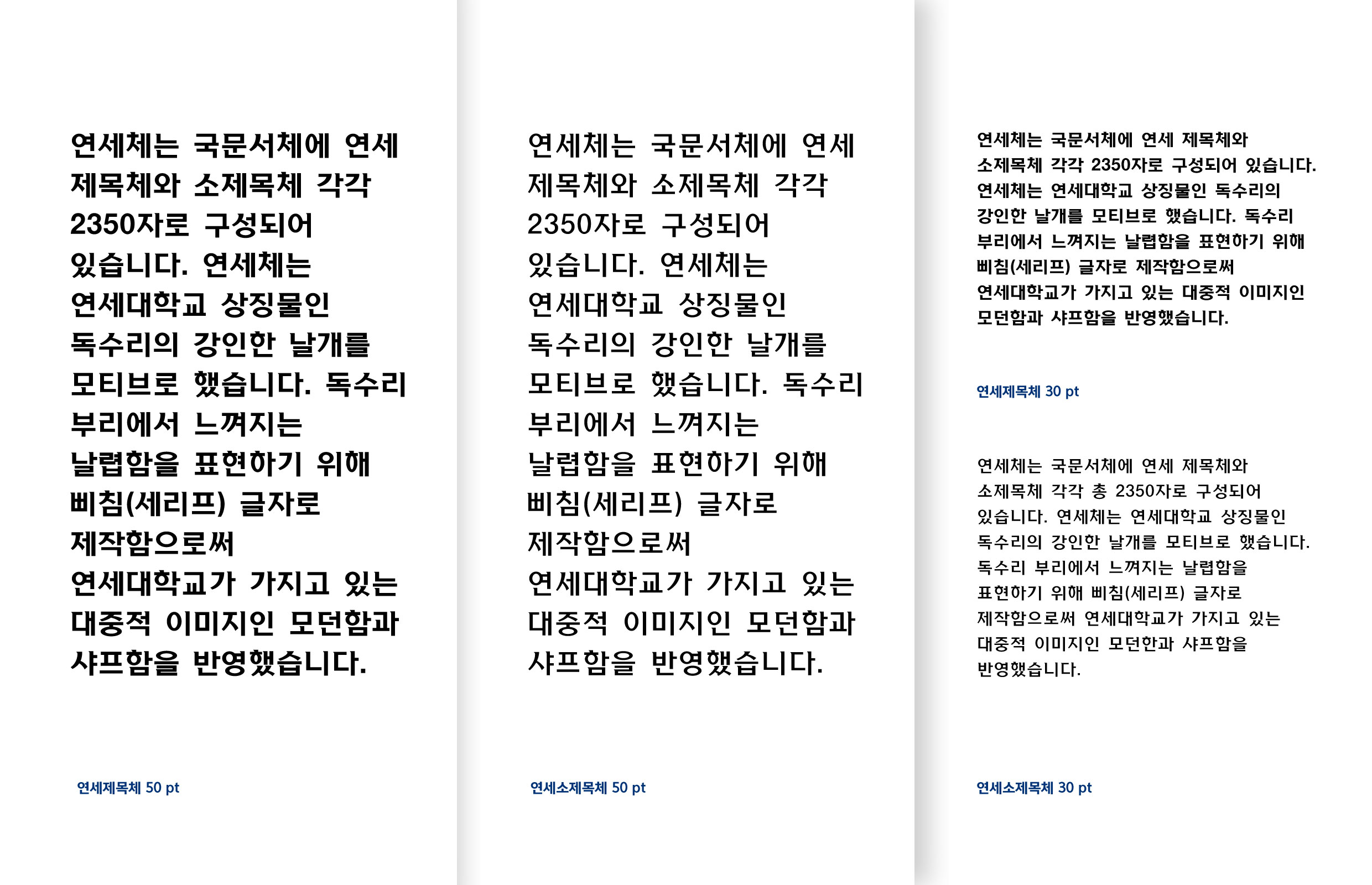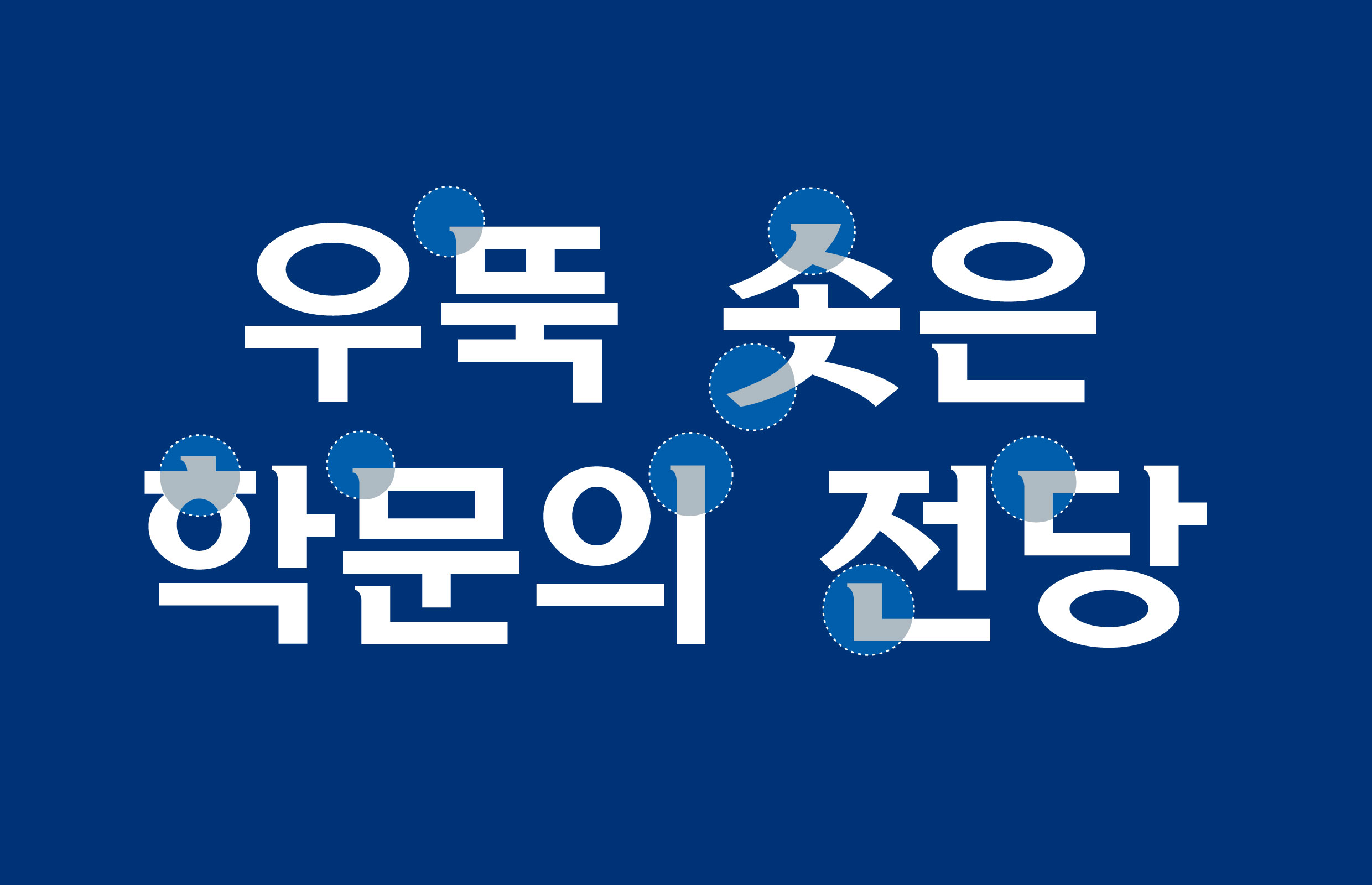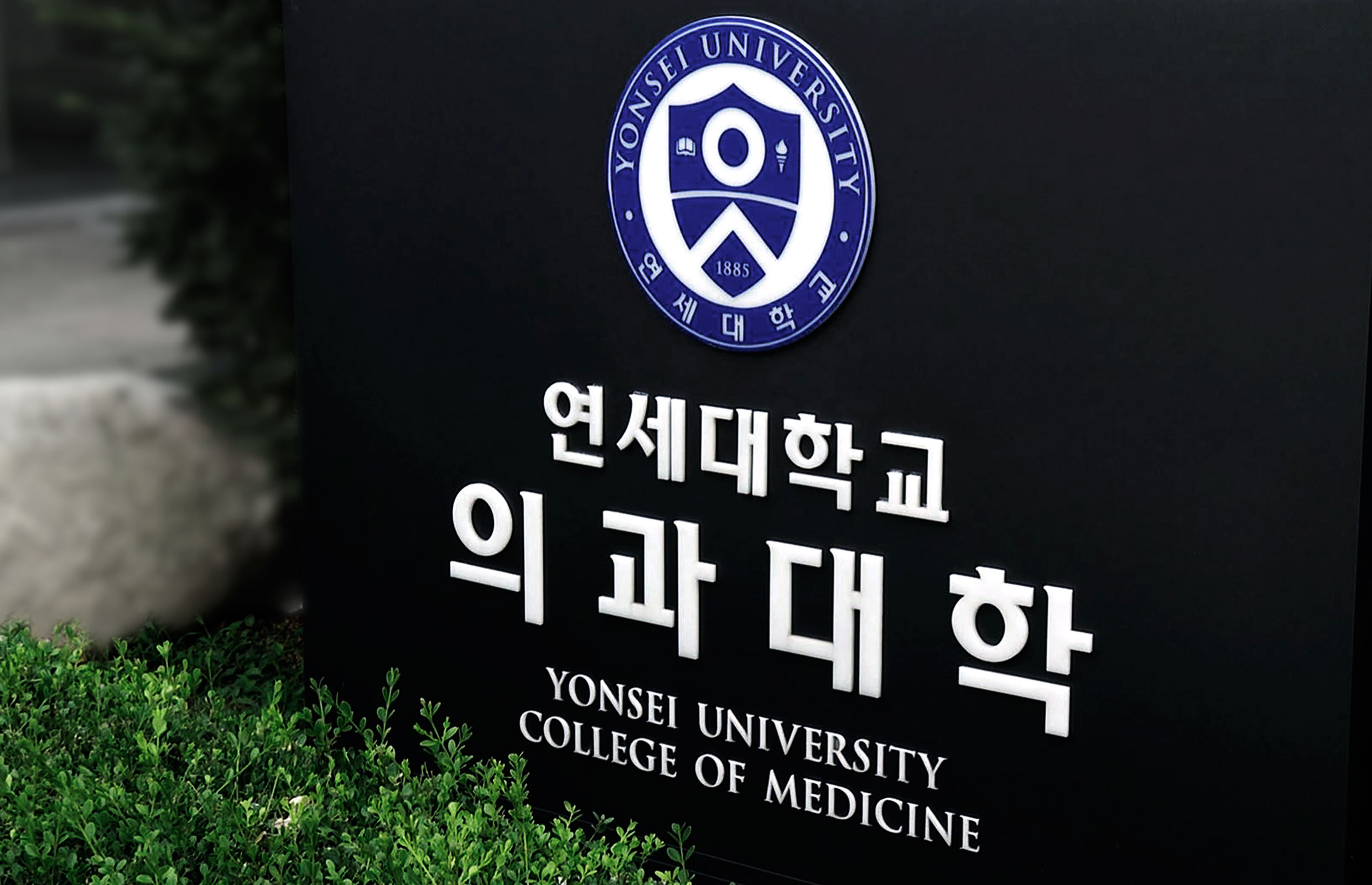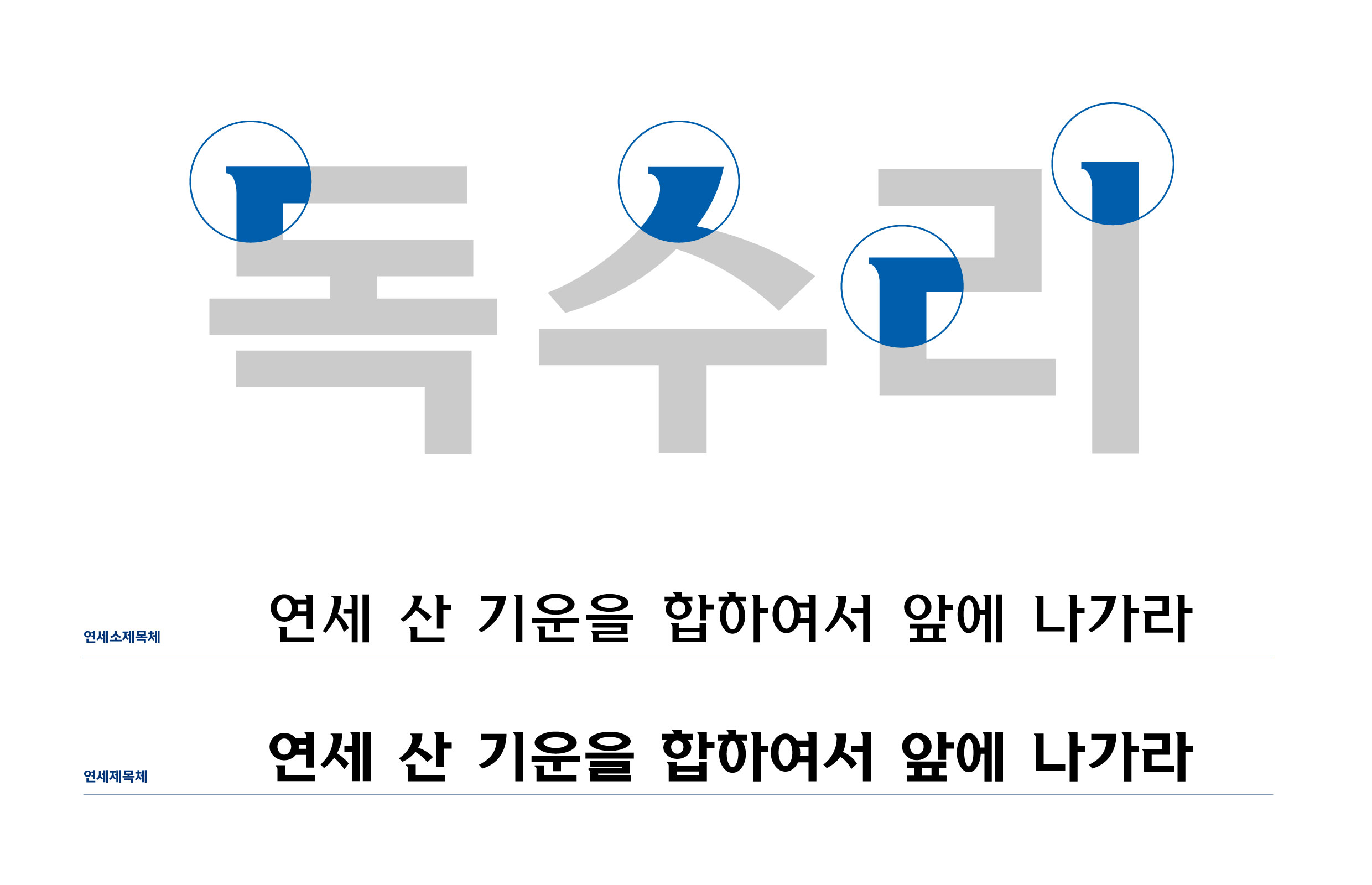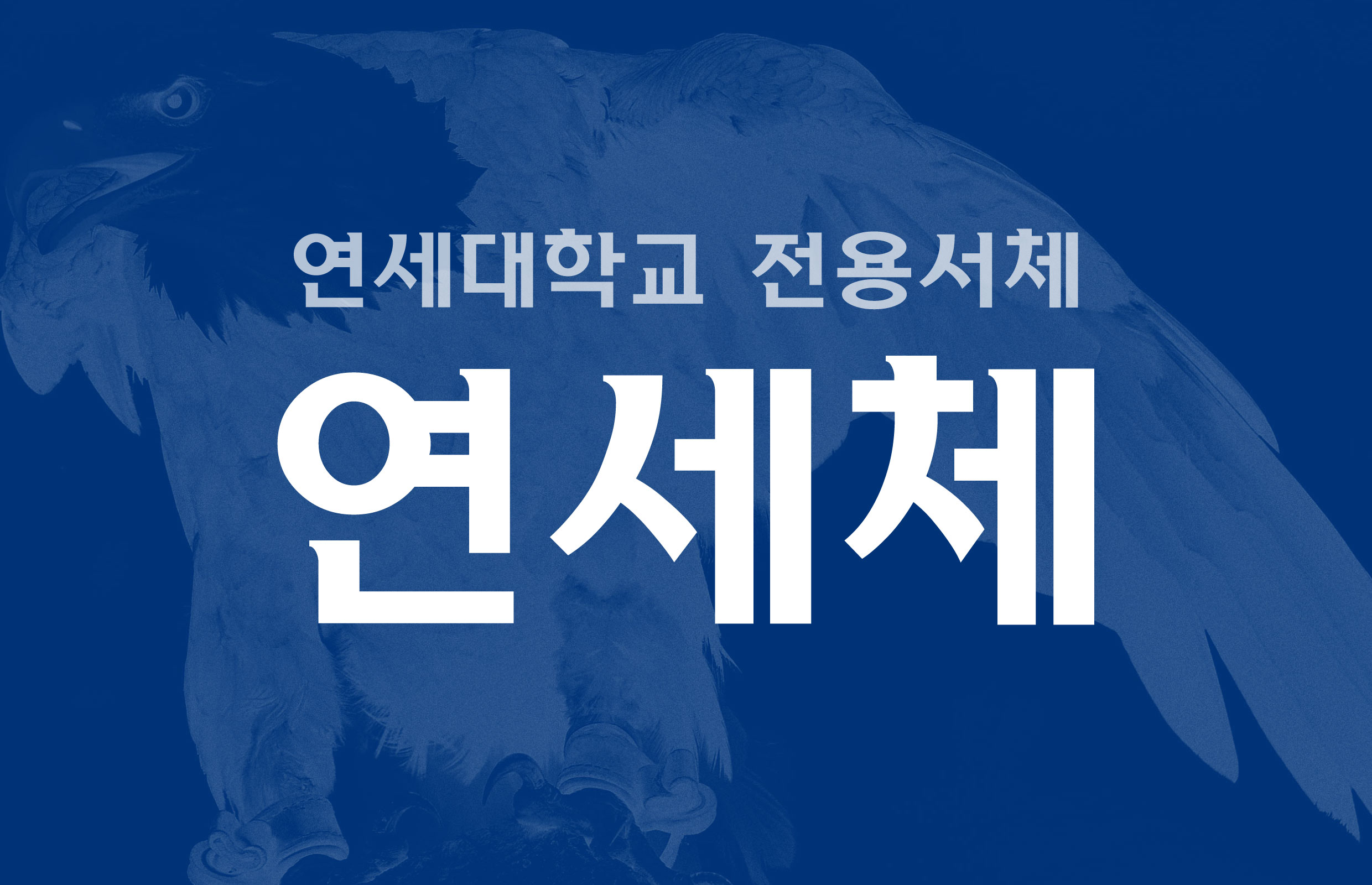
연세대학교 [연세체]
연세대학교는 대학 아이덴티티(UI) 교체 작업과 함께 연세체를 발표했다. 연세체는 연세대학교 상징물인 독수리의 강인한 날개를 모티브로, 독수리 부리에서 느껴지는 날렵함을 표현하기 위해 삐침(세리프) 글자로 제작했으며, 연세대학교가 가지고 있는 대중적 이미지인 모던함과 샤프함을 반영하였다.